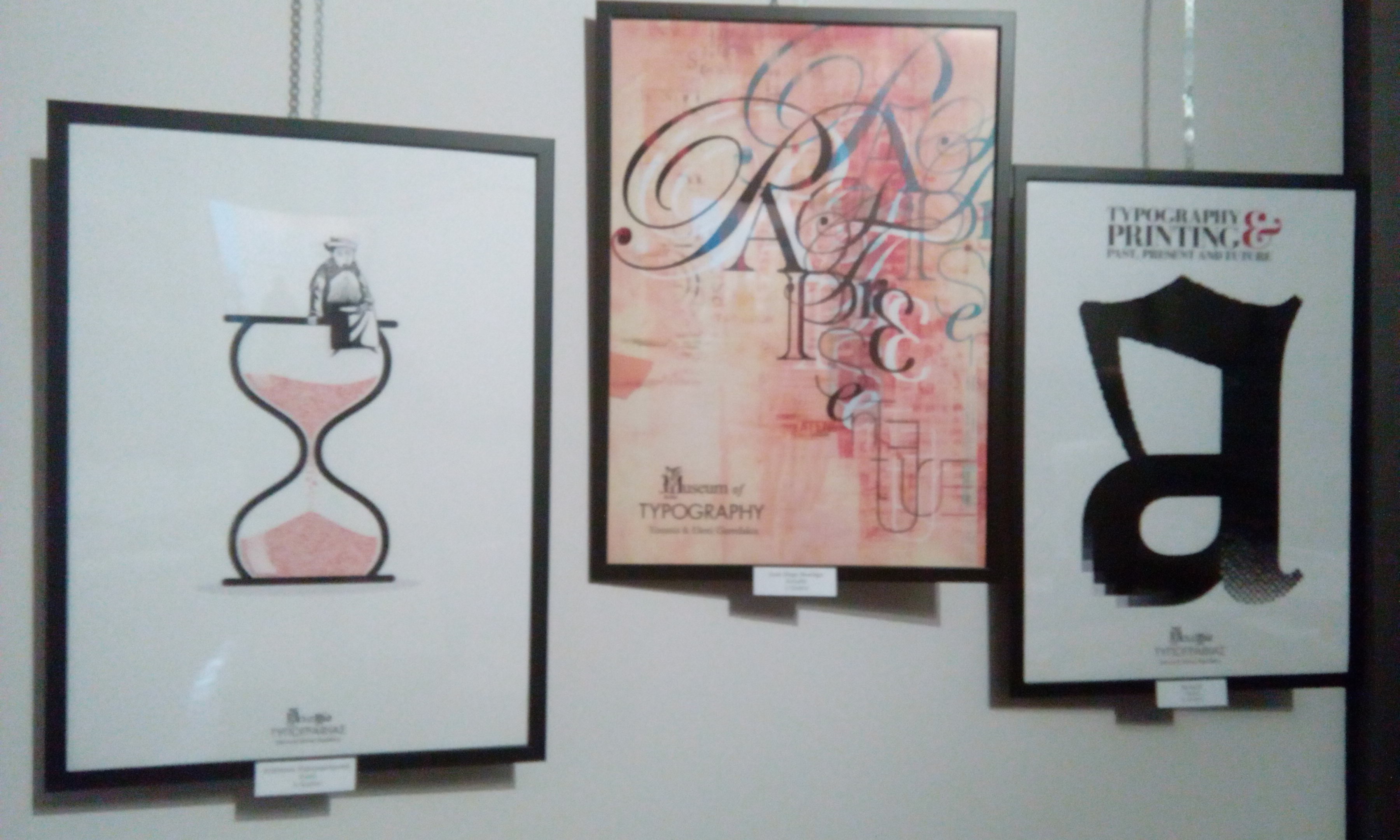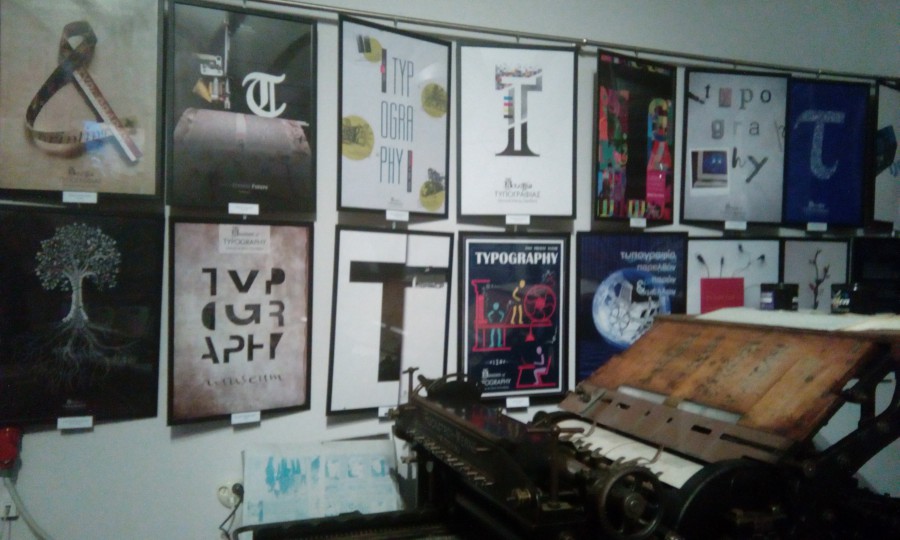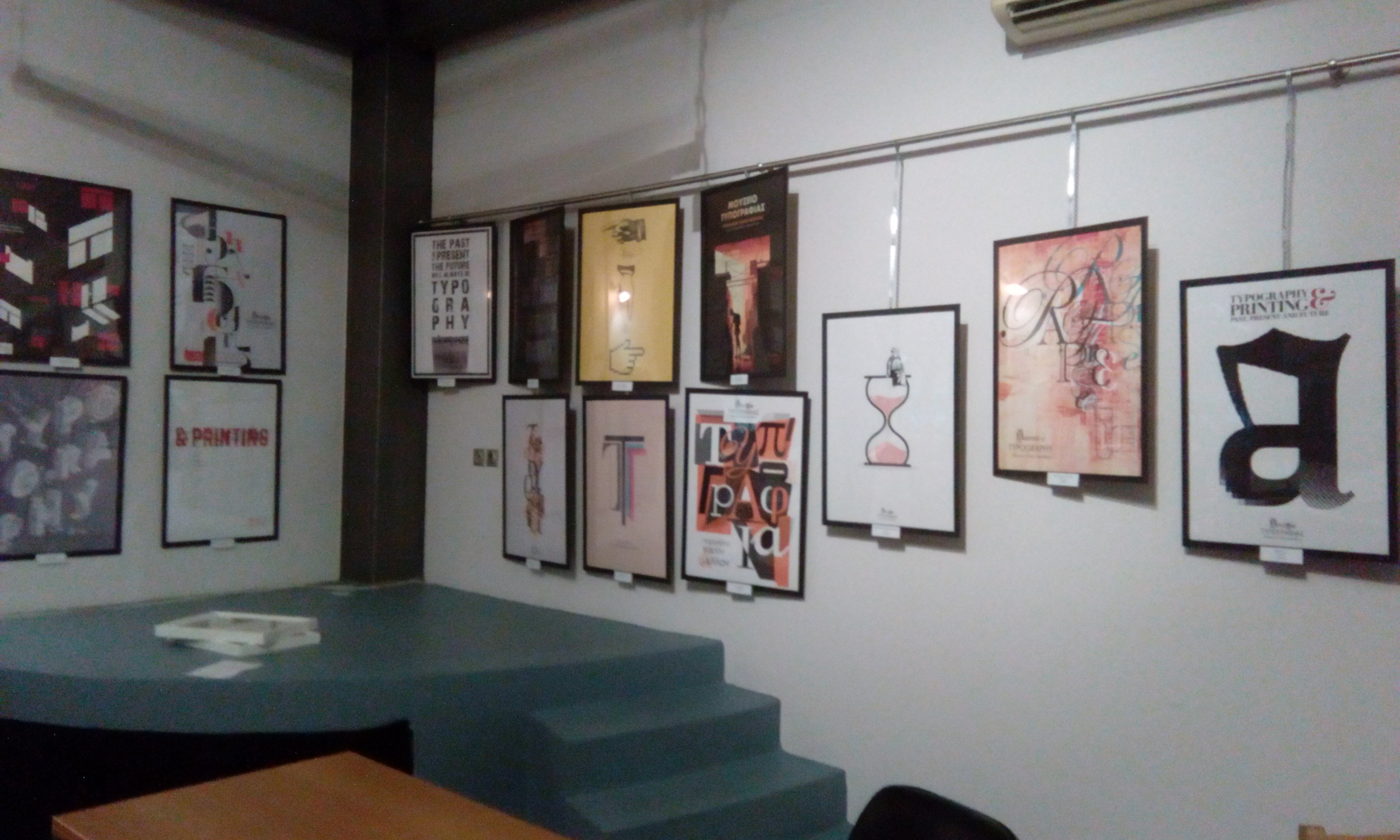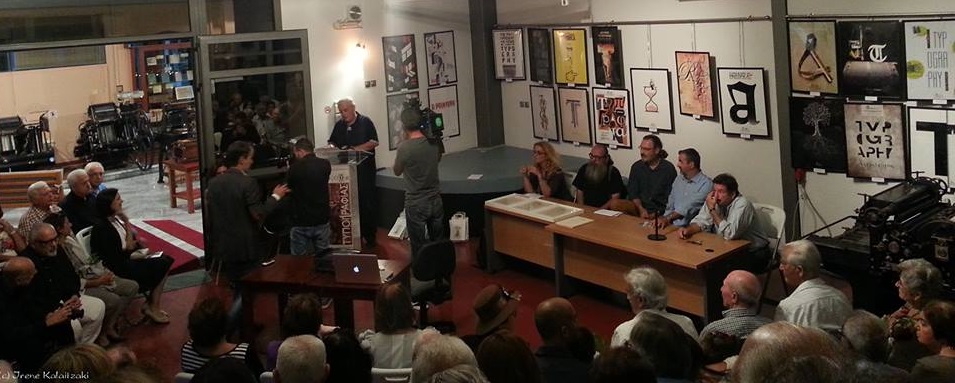
«Το Μουσείο Τυπογραφίας ”αγκαλιάζει’’ την ιστορία των πρώτων Κρητών τυπογράφων που αφοσιώθηκαν στην εκτύπωση των πρώτων ελληνικών βιβλίων ώστε το Γένος να μην χαθεί κάτω από από την Οθωμανική Αυτοκρατορία» , επεσήμανε ο αρχιτέκτων, ιστορικός του βιβλίου, Κωνσταντίνος Στάικος μιλώντας για τις απαρχές της ελληνικής τυπογραφίας στο πλαίσιο της απονομής των βραβείων του 3ου διεθνή διαγωνισμού αφίσας που πραγματοποιήθηκε το βράδυ του Σαββάτου στο αμφιθέατρο του Μουσείου Τυπογραφίας.
Στον διαγωνισμό αφίσας με θέμα “Τυπογραφία: Παρελθόν, παρόν και μέλλον” υπήρξαν 252 συμμετοχές από τις πέντε ηπείρους και κάθε γωνιά της Ελλάδας. Οι τριάντα καλύτερες αφίσες που επιλέχθηκαν από την κριτική επιτροπή έλαβαν τιμητικές διακρίσεις ενώ τρία έργα έλαβαν σημαντικότατα χρηματικά έπαθλα (1000 ευρώ ο πρώτος, 700 ευρώ ο δεύτερος και 500 ευρώ ο τρίτος, χορηγία της εφημερίδας “Χανιώτικα νέα”).
ΤΑ ΒΡΑΒΕΙΑ ΚΑΙ ΟΙ ΔΙΑΚΡΙΣΕΙΣ
Το πρώτο βραβείο έλαβε ο Juan Diego Restrepo από την Κολομβία ο οποίος μέσω βιντεοσκοπημένου μηνύματος εξέφρασε τις ευχαριστίες του διότι, όπως είπε, το Μουσείο Τυπογραφίας έδωσε την ευκαιρία σε ανθρώπους των γραφικών τεχνών να παρουσιάσουν την δουλειά τους ακόμη και στην άλλη άκρη της γης. Το δεύτερο βραβείο έλαβε ο Murat Cil από την Κωνσταντινούπολη, ο οποίος δεν μπόρεσε να παρεβρεθεί καθώς από την Τουρκία δεν του δόθηκε η δυνατότητα να βγάλει διαβατήριο. Το τρίτο βραβείο έλαβε ο Ευάγγελος Καλογηρόπουλος από τα Χανιά ο οποίος και ευχαρίστησε το Μουσείο Τυπογραφίας.
Αξίζει να αναφερθεί πως αρκετοί δημιουργοί που διακρίθηκαν για τις αφίσες τους ταξίδεψαν από το εξωτερικό και την υπόλοιπη Ελλάδα στα Χανιά ειδικά για την εκδήλωση. Τιμητικές διακρίσεις έλαβαν οι Αίαντας Κόκκαλης, Δημήτρης Αποστολίδης, Αργύρης Αθανασιάδης, ο Igor Bendas, Silvia Casado del Rio, Ιωάννης Τσιαμαντάς, Kamen Goranov, Δανάη Πετάση, Barbora Matlovicova, Jana Pomykacova, Κωνσταντίνος Κρίγκας, Olivera Batajic, Δημήτρης Μπούκος, Γεράσιμος Χωραίτης, Σπύρος Πιττίδης, Άγγελος Γουναρίδης, Yan Zhou, Αλίκη Μαργαρού, Πολυξένη Λουκά, Μάρκελλος Κολοφωτιάς, Marton Borbas, Carl Godfrey, Σπύρος Καμποσούλης, Matias Azevedo, Erick Ginard, Alison Watson, Andrea Barkhuize, Μιχάλης Μπα’ι’ρακτάρης, Γεώργιος Κρητικός, Τυπογραφείο Στοιχειάγρα.
ΟΙ ΔΡΑΣΕΙΣ ΤΟΥ ΜΟΥΣΕΙΟΥ ΠΡΟΒΑΛΛΟΥΝ ΤΑ ΧΑΝΙΑ
Ο εμπνευστής και ιδρυτής του Μουσείου Τυπογραφίας Γιάννης Γαρεδάκης, επεσήμανε πως με την συγκεκριμένη εκδήλωση το Μουσείο Τυπογραφίας επιβεβαιώνει, ότι δεν θα παραμείνει απλά ένας μουσειακός χώρος. Διεκδικεί – και ως ένα σημείο το έχει επιτύχει- να είναι και χώρος για ποικίλες εκδηλώσεις πολιτισμού, χώρος δημιουργικός. Παράλληλα τόνισε ότι μέσα από τις δράσεις του Μουσείου προβάλλονται και τα Χανιά.
Για την εντυπωσιακή συμμετοχή του τρίτου διαγωνισμού αφίσας, μίλησε η διευθύντρια του Μουσείου Έλια Κουμή, η οποία τόνισε ότι με τις δράσεις που έχει αναπτύξει τα τελευταία χρόνια το Μουσείο προβλήθηκε πανελλήνια αλλά και διεθνώς. Άλλωστε αυτό αποδεικνύεται και από το γεγονός ότι ο φετινός διεθνής διαγωνισμός αφίσας ολοκληρώθηκε με ρεκόρ συμμετοχών από κάθε μήκος και πλάτος της Γης και φυσικά από κάθε άκρη της Ελλάδας.
Χαιρετισμούς απηύθηναν τα μέλη της κριτικής επιτροπής Γιώργος Ματθιόπουλος, καθηγητής Εφαρμογών στο Τμήμα Γραφιστικής της Σχολής Καλλιτεχνικών Σπουδών του ΤΕΙ Αθηνών, Αλέξανδρος Κοκκόλας, γραφίστας, καθηγητής Γραφιστικής στο Κολέγιο Βακαλό και Ελένη Σταυρίδη, γραφίστρια της εφημερίδας ‘’Χανιώτικα νέα’’.
Ο Γ. Ματθιόπουλος, επεσήμανε ότι σε κάθε έκθεμα, σε κάθε μηχάνημα, σε κάθε έντυπο του Μουσείου Τυπογραφίας συναντιώνται οι Τέχνες, τα Γράμματα με την Τέχνη των Επιστημών. Παράλληλα ανέφερε ότι ένα σημαντικό πεδίο της Τυπογραφικής Τέχνης είναι η οπτική επικοινωνία με την μορφή της αφίσας, η οποία αποτελεί ουσιαστικά ένα έργο Τέχνης.
Ο Αλέξανδρος Κοκκόλας, γραφίστας, καθηγητής Γραφιστικής στο Κολέγιο Βακαλό, ο οποίος επισκέπτεται κάθε χρόνο με τους μαθητές του το Μουσείο Τυπογραφίας στο πλαίσιο τριήμερης εκπαιδευτικης εκδρομής, έκανε λόγο για ένα χώρο που έχει δημιουργηθεί με πολύ κόπο, αγάπη και μεράκι, δίνοντας την ευκαιρία στα νέα παιδιά να μάθουν για την ιστορία της Τυπογραφίας μέσα στους αιώνες.
Η Ελένη Σταυρίδη, γραφίστρια της εφημερίδας ‘’Χανιώτικα νέα’’ επεσήμανε ότι μέσα στις αίθουσες του Μουσείου γιορτάζει αποκλειστικά και μόνο η Τυπογραφία. Γιατί ο χώρος αυτός αρχικά δεν δημιουργήθηκε για να γίνει Μουσείο: οι αίθουσες του έχουν τις μυρωδιές και τα χρωματα του μελανιού και του φρέσκου χαρτιού αφού αρχικά είχε φιλοξενήσει τις εγκαταστάσεις της εφημερίδας Χανιώτικα νέα. Για αυτό τον λόγο, ο χώρος τούτος δεν θα είναι ποτέ απλά ένα Μουσείο.
Χαιρετισμό επίσης απηύθηνε και ο Διευθυντής των Χανιώτικων νέων Παρασκευάς Περάκης σημειώνοντας ότι το πίσω από το Μουσείο Τυπογραφίας κρύβεται το πάθος για μια Τέχνη, πάθος για δημιουργία, επισημαίνοντας ότι η εφημερίδα Χανιώτικα νέα ‘’αγκαλιάζει’’ κάθε δράση του Μουσείου γιατί ουσιαστικά αγκαλιάζει κάθε δημιουργική δραστηριότητα, κάτι που θα συνεχίσει να κάνει και στο μέλλον.
‘’ Η ιστορία της ελληνικής τυπογραφίας, είναι θέμα Κρητικό’’
Κάνοντας μια ιστορική αναδρομή στις απαρχές της ελληνικής τυπογραφίας, ο Κωνσταντίνος Στάικος, αρχιτέκτων, ιστορικός του βιβλίου, τόνισε ότι το Μουσείο Τυπογραφίας δεν είναι απλώς ένα Μουσείο καθώς «εδώ η ύλη συναντά τον δημιουργό της. Δηλαδή τους Κρήτες τυπογράφους οι οποίοι ουσιαστικά ‘βάλαν την σφραγίδα τους και η ιστορία της ελληνικής τυπογραφίας, τουλάχιστον οι απαρχές, είναι θέμα Κρητικό».
Το ‘’παρών’’ στην εκδήλωση έδωσαν μεταξύ άλλων ο θεματικός Αντιπεριφερειάρχης Παιδείας Παν. Σημανδηράκης, ο δήμαρχος Αποκορώνου Χαρ. Κουκιανάκης, ο πρώην βουλευτής Χρ. Δαμιανάκης, ο πρώην πρύτανης του Πολυτεχνείου Γ. Φίλης, οι δημοσιογράφοι Μαν. Αναγνωστάκης, Κώστας Μπετινάκης κ.α